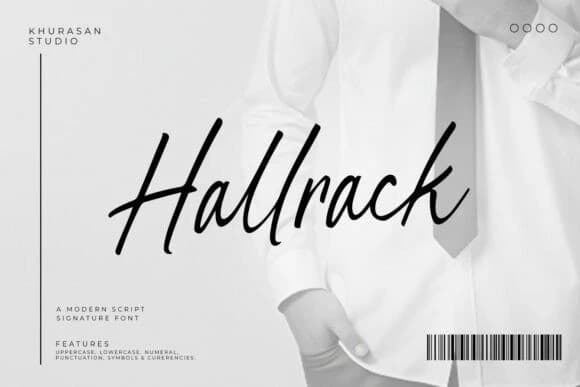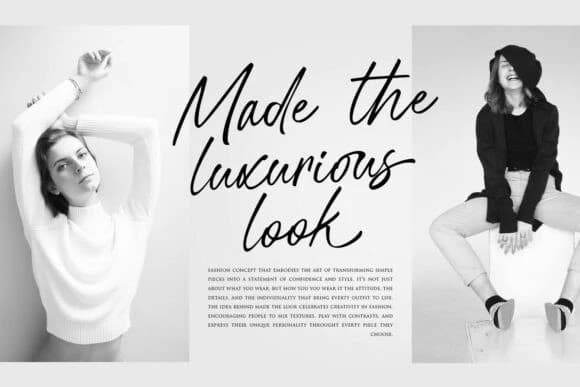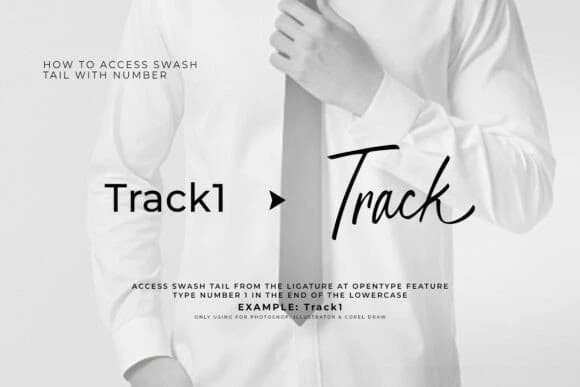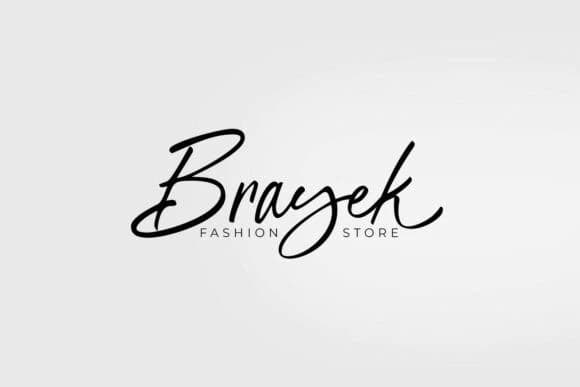
Hallrack Script Font
Hallrack Script Font, doğal fırça etkisiyle bir script el yazısı fontudur ve gerçek el yazısının güzelliğini yakalamak için tasarlanmıştır. Her bir çizgi canlı hissedilir — akıcı, ifade gücü yüksek ve karakter dolu. O, tasarımlarınıza otantik bir el yazısı çekiciliği sunar ve tasarımlarınızı sıcak,
Hallrack Script Font, doğal fırça etkisine sahip bir kaligrafi el yazısı fontudur ve gerçek el yazısının güzelliğini yakalamak için tasarlanmıştır. Her bir vuruş canlı hissedilir — akıcı, ifade dolu ve kişiliğiyle dolu. Gerçek el yazısı cazibesini sunar ve tasarımlarınıza sıcak, şık ve premium bir hava katar.